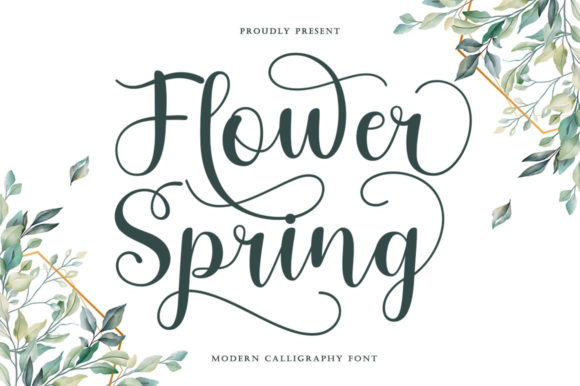
Flower Spring Font
適切なデザイン要素を見つけるのは難しい場合がありますが、Flower Spring Fontは作品を即座に引き立てる優れたコレクションを提供します。
POD(オンデマンド印刷)製品、結婚式の招待状、またはソーシャルメディアのグラフィックを作成している場合でも、Flower Spring Fontは理想的です。